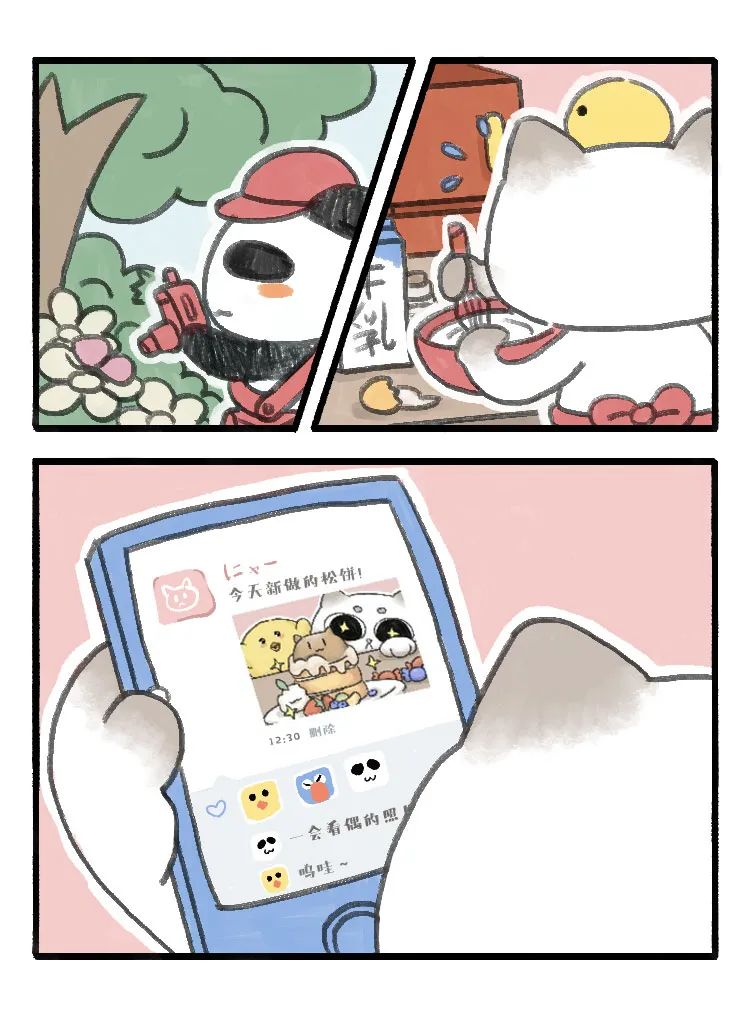
这对字体太可爱了,我都想磕CP了~
它们都是刚柔并济的couple,不过也有那么一对companion,甜甜蜜蜜、可可爱爱,看一眼心都化了。
真猫CP
小熊猫和纯真猫是一对神奇的小伙伴,虽然住得很近,但由于一个爱玩,一个爱宅,所以很少见面。直到有一天,纯真猫采购回家,正好遇上拿着行李箱的小熊猫,它们便火热地聊起来,还互加了微信。
你每天去那么多地方,不累吗?
不会啊,因为大千世界太精彩了,我乐在其中。
那你每天都呆在家里,不无聊吗?
当然不,因为做美食是我最喜欢的事情,我很有成就感。
……
它们彼此分享着各自生活的点点滴滴,感受着不曾经历的世界,幸福而互补。
点字纯真体
这天,纯真猫分享了一个松饼的食谱,从选材到过程都很讲究,光看着都是一种享受了。
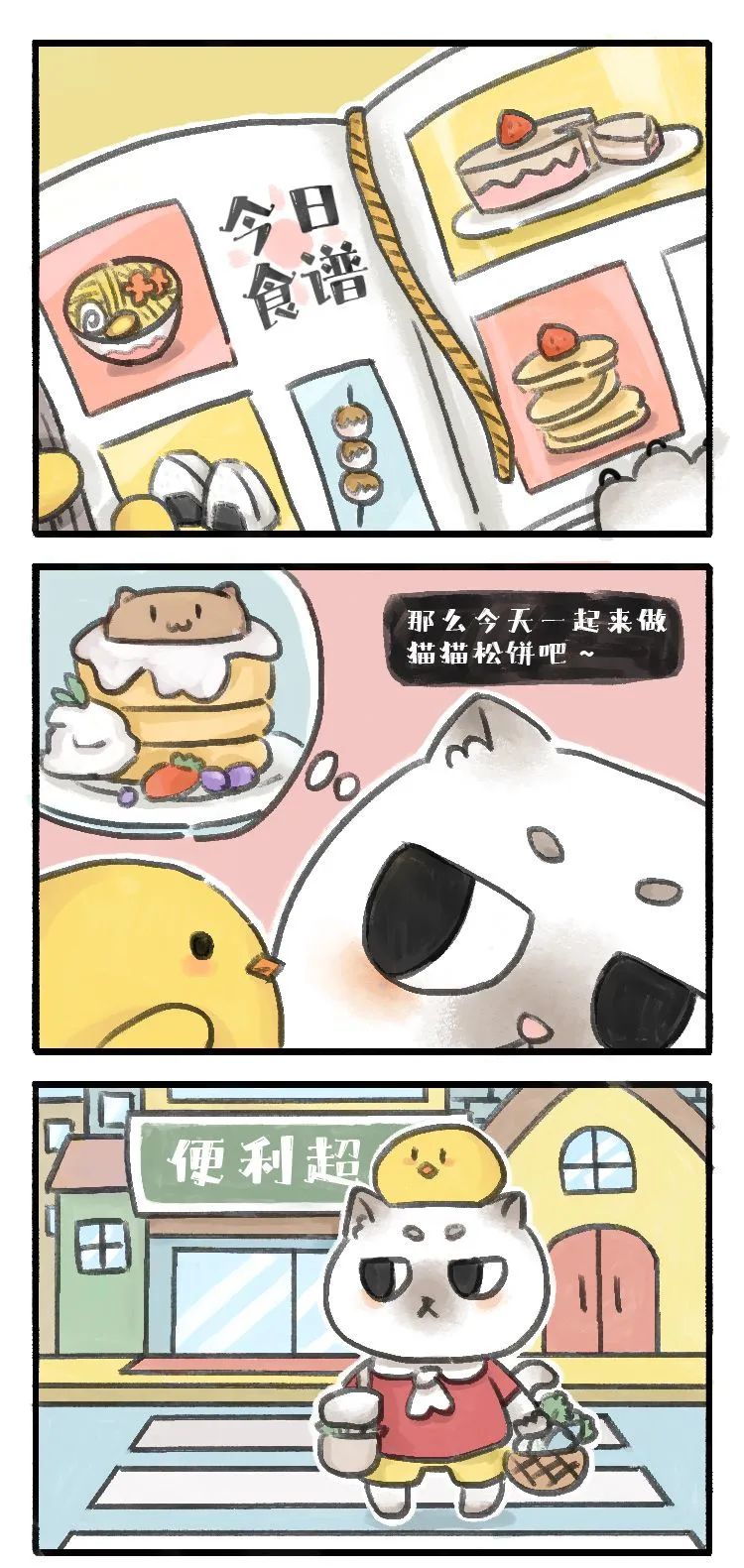
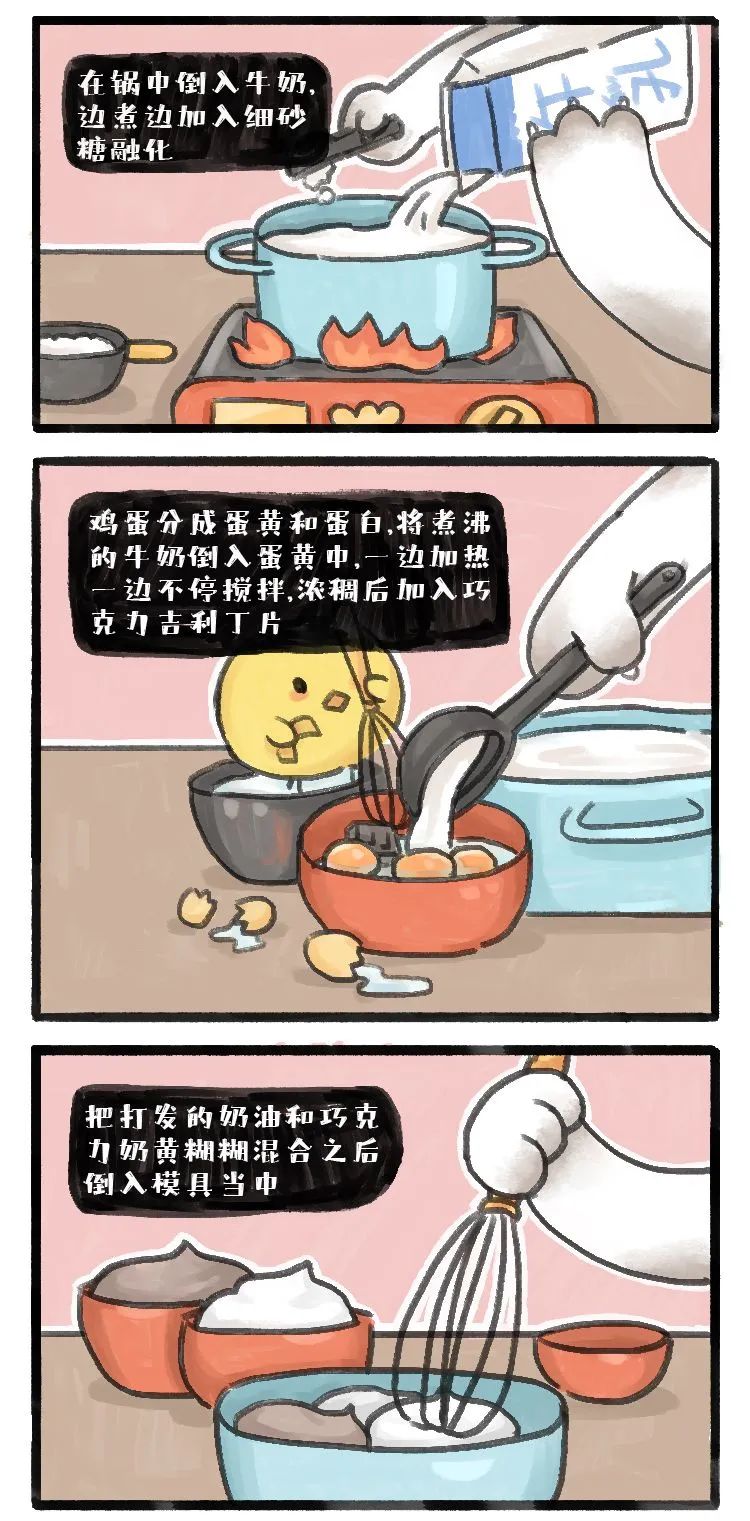
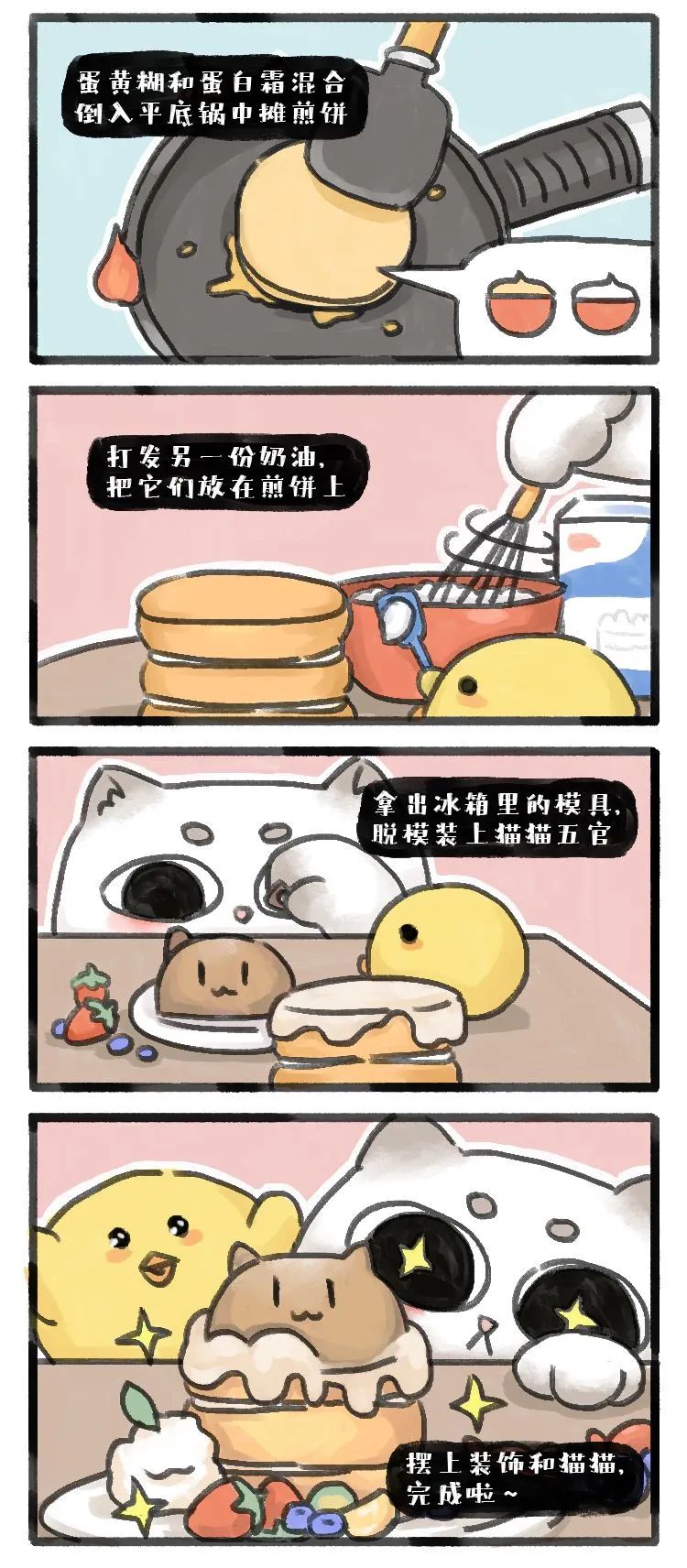
点字小熊猫
而小熊猫也不甘示弱,分享了自己在世界各国的美食奇遇记……
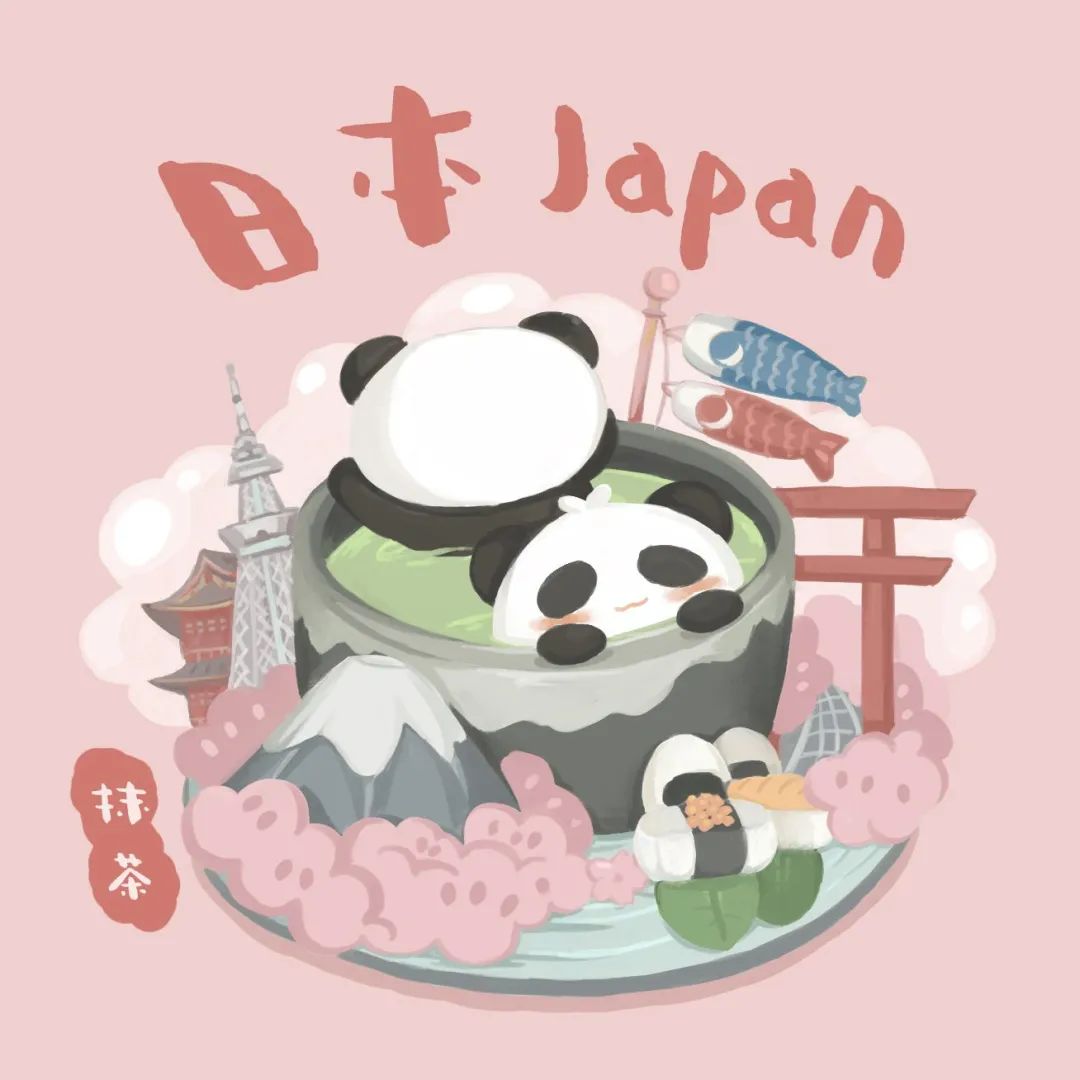
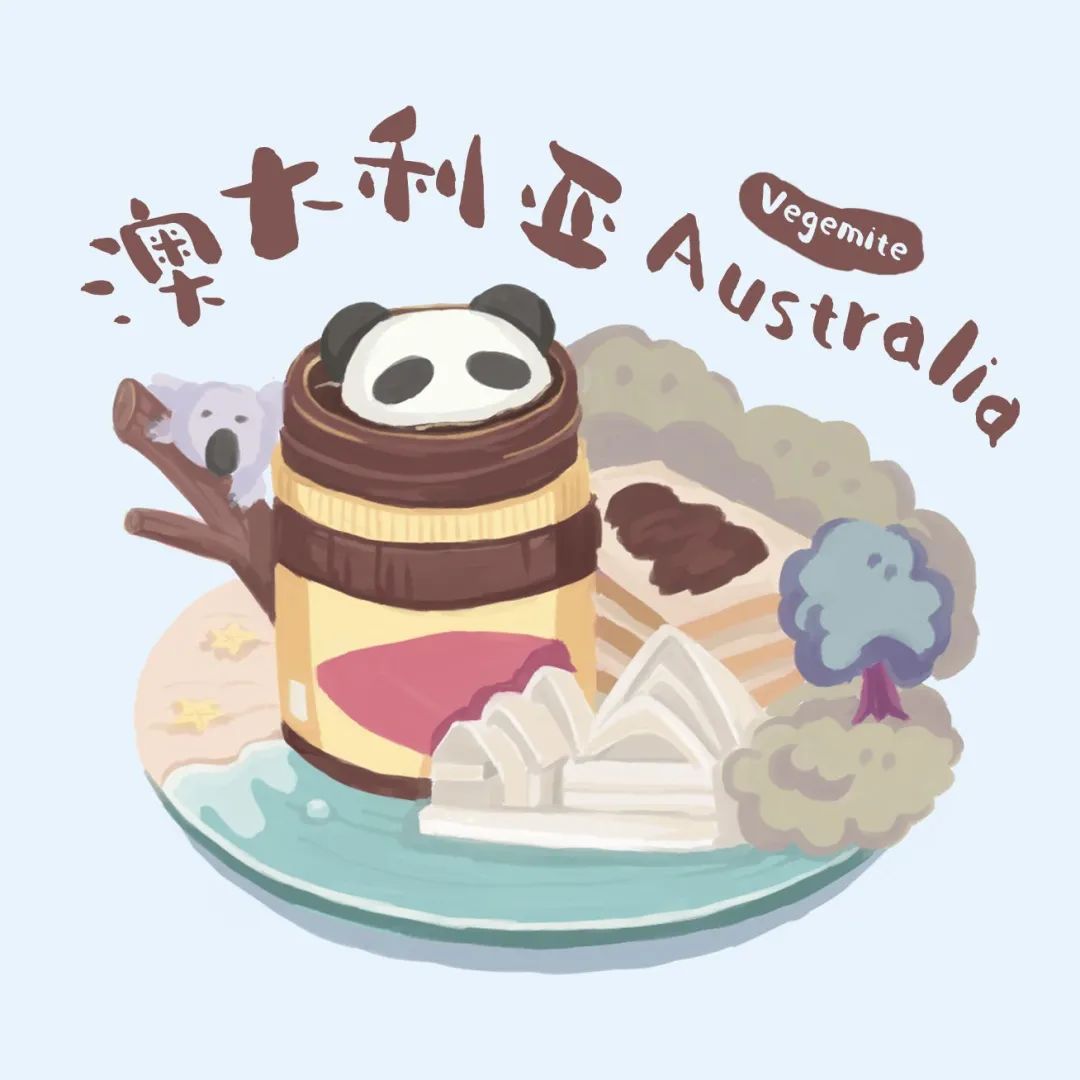
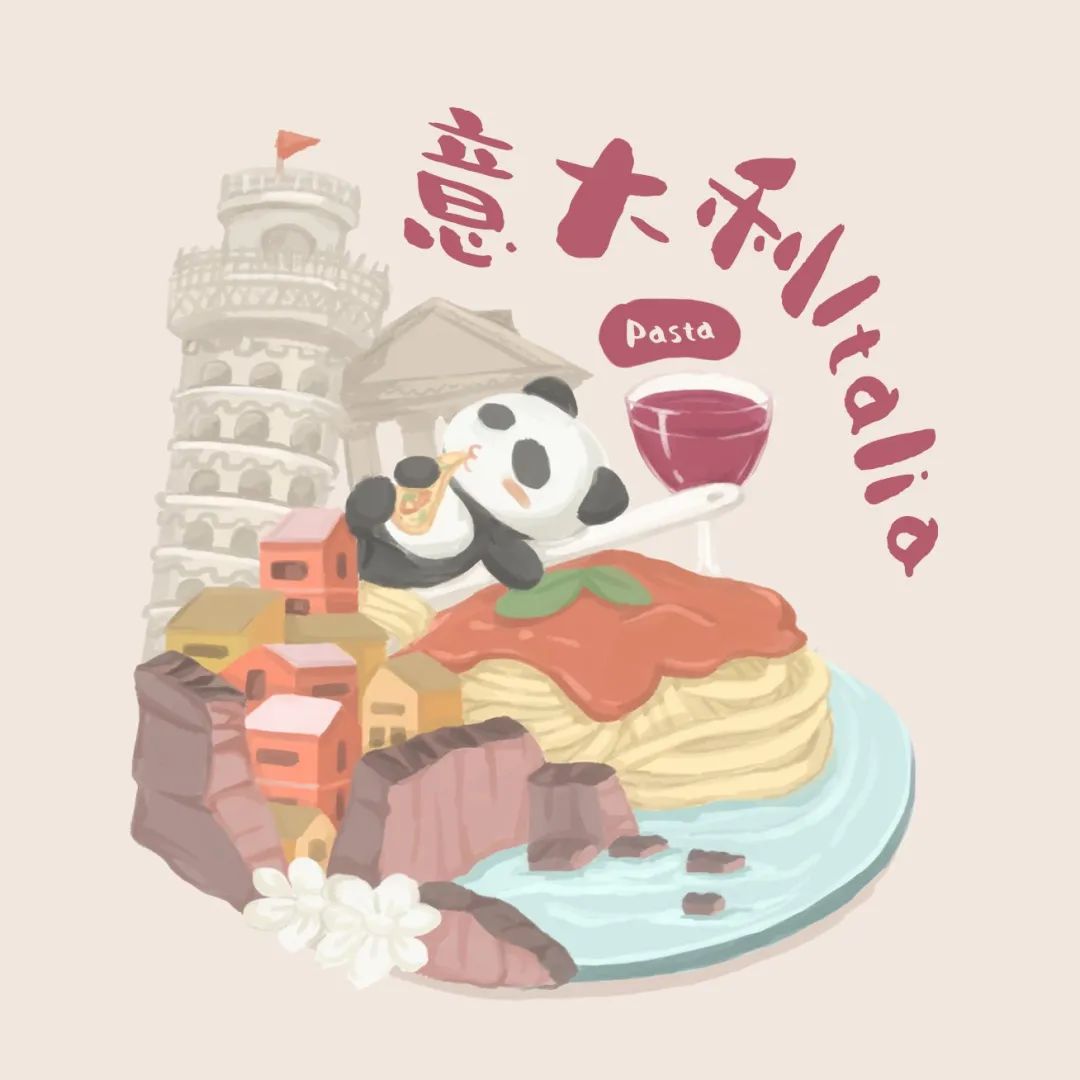
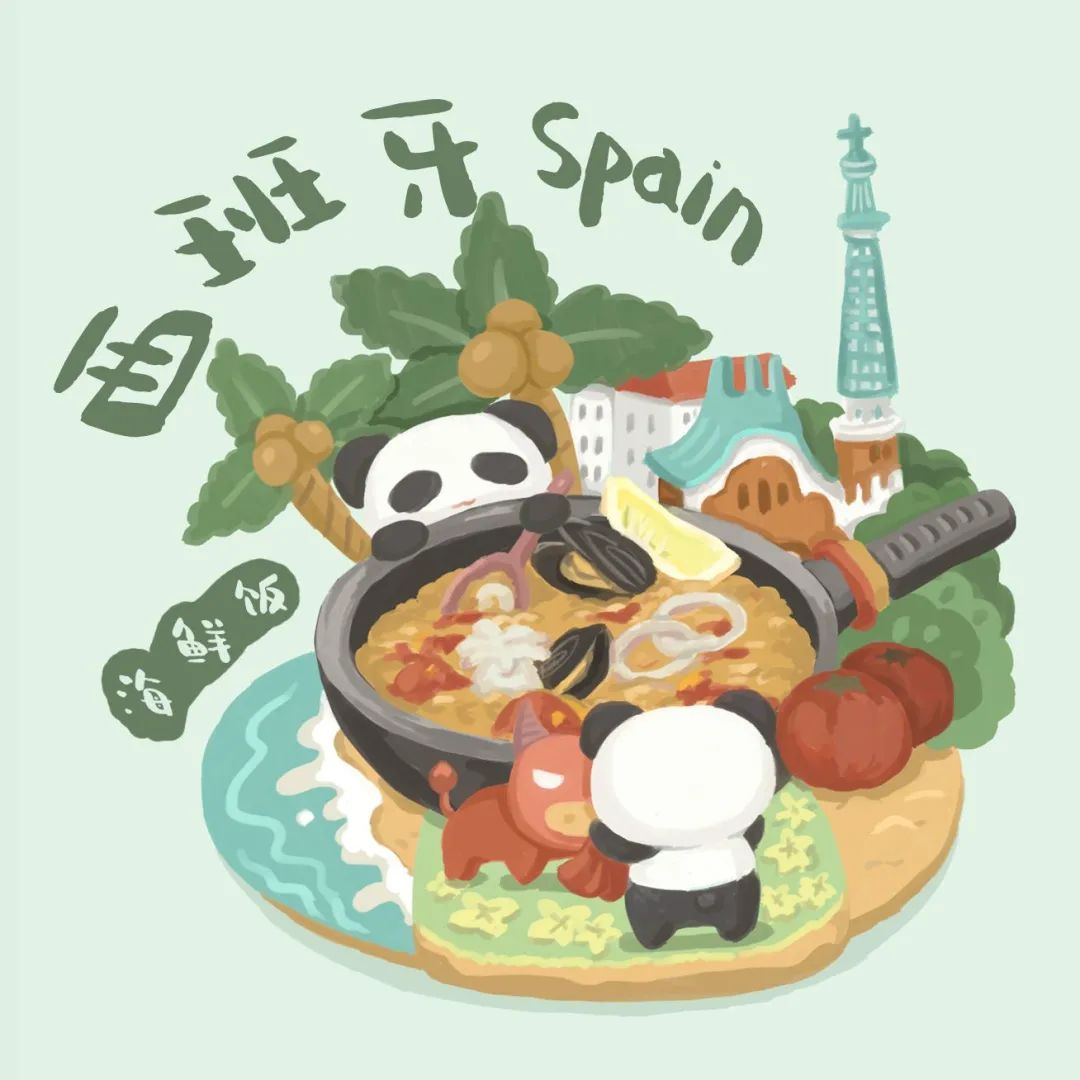
这对companion的故事还在上演,但有一个方法,可以更近距离接触它们,那就是使用专属字体。